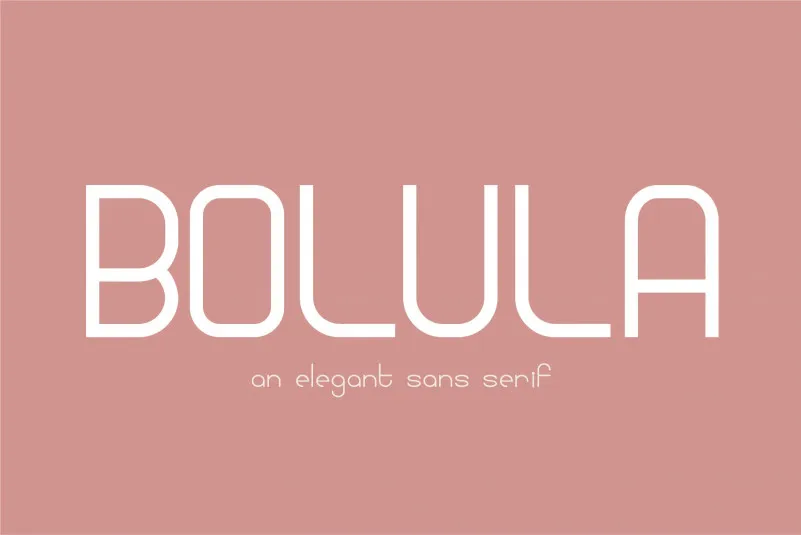
Bolula Sans Serif Font – Fonte Grátis
Bolula Sans Serif Font
Esta é uma fonte moderna sem serif desenvolvida pelo White Supply. Ela foi projetada especificamente para estilos minimalistas, idealmente para aplicativos como postais de festival, títulos de filmes e editoriais com um forte impacto visual. Introduzimos a Bolula Font. Esta é uma fonte sans-serif elegante, simples e leve que funciona perfeitamente para tornar qualquer projeto gráfico em algo sofisticado. A Bolula Sans Serif é ótima tanto para projetos de marca como para criações de móveis e embalagens, cabeçalhos de revistas ou até mesmo como overlay estilizado de texto sobre imagens de fundo.